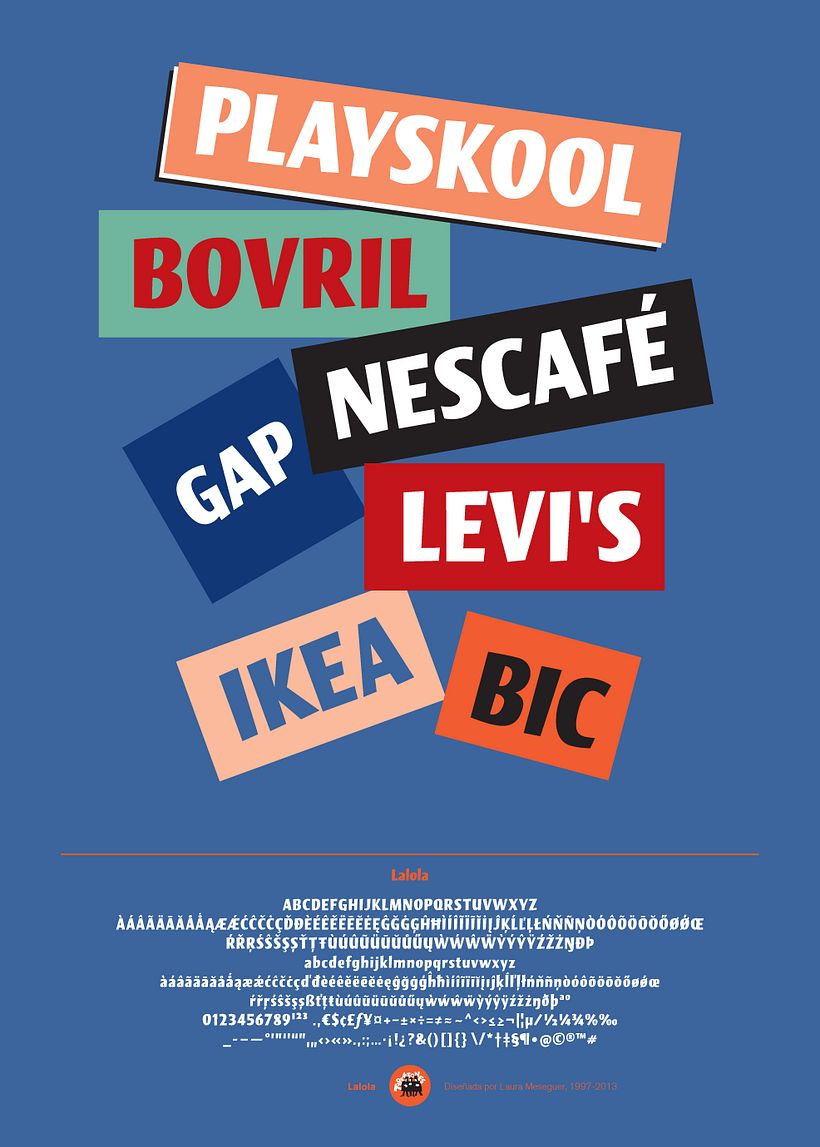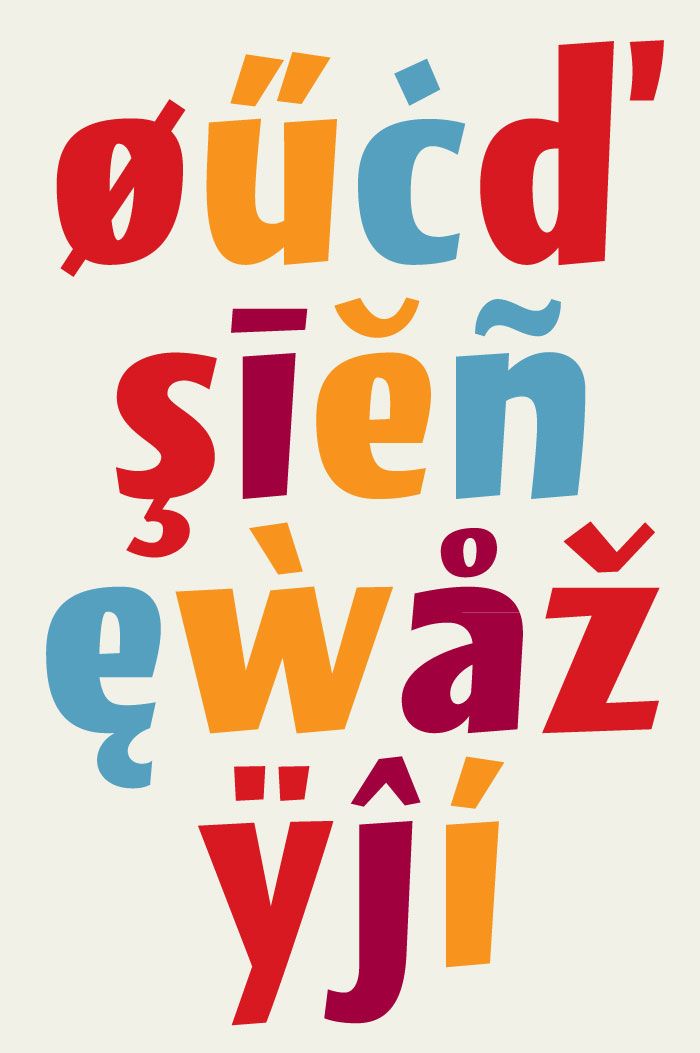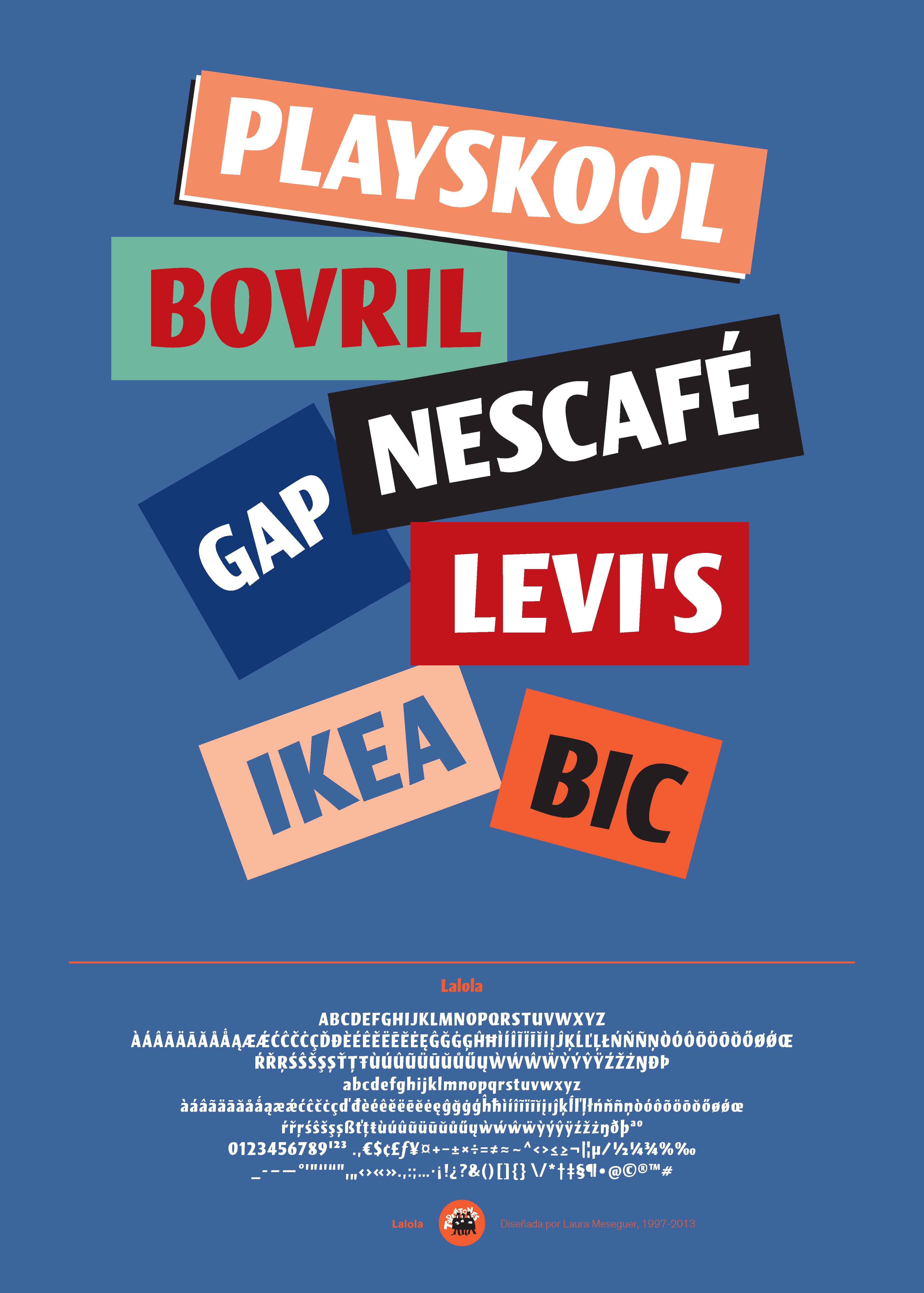
Lalola, una tipografía display con fuerte carácter
Lalola (antes Lola) es una tipografía para títulos inspirada en un modelo encontrado en un libro de Eugen Nerdinger y Lisa Beck. Lalola tomó como punto de partida algunas de las pocas letras disponibles en el modelo, para convertirse en un tipo con carácter fuerte y mucha personalidad, útil cuando se necesitan palabras en voz alta. El set de caracteres cubre las necesidades del alfabeto latino, las lenguas centroeuropeas , bálticas y el turco.
‘Where others need a gazillion of weights, glyphs and lines of OpenType feature code to make a font lively, Laura Meseguer only needs one slim font’. —Typefacts